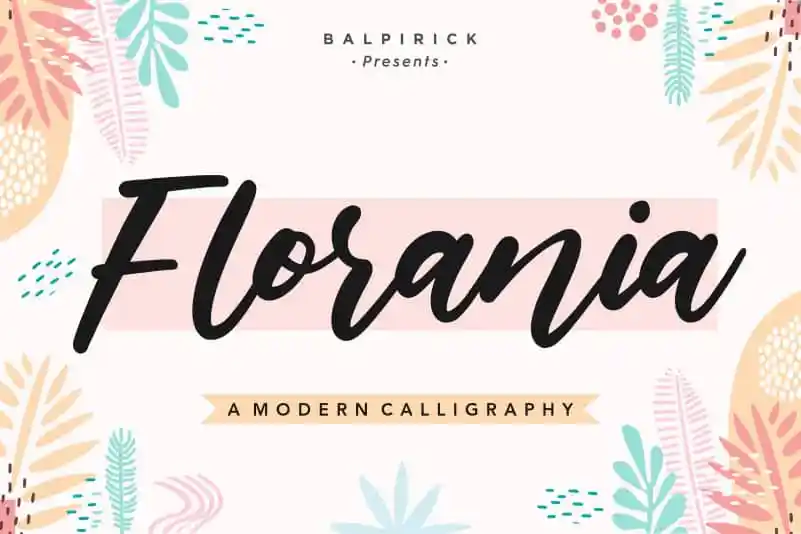
Florania Calligraphy Font – Fonte Grátis
Florania Calligraphy Font
A Florania Calligraphy Font é perfeitamente adequada para diversos projetos digitais e presenciais, seja em embalagens de produtos, criação de marca, revistas ou redes sociais. Sua elegância e delicadeza a tornam uma opção ótima para expressar um título ao fundo de uma página de publicação. Perfeita também para eventos românticos como casamentos, Florania oferece aquela textura sofisticada que você procura. Além disso, é muito versátil e pode ser utilizada em qualquer projeto onde desejar adicionar elegância à sua mensagem. Uma escolha perfeita para quem busca uma fonte de qualidade para expressar palavras ao fundo de um design, seja no mundo digital ou do papel. Além das possibilidades acima, a Florania também é ideal para aqueles que desejam expressar textos de forma criativa e única em seus projetos. Sua graciosidade e harmonia torna-a uma fonte valiosa não só para designers, mas também para quem simplesmente quer deixar um toque especial nas suas criações digitais ou impressas. Seja no ambiente digital ou físico, Florania é uma fonte que sempre dará um toque de classe a qualquer projeto.